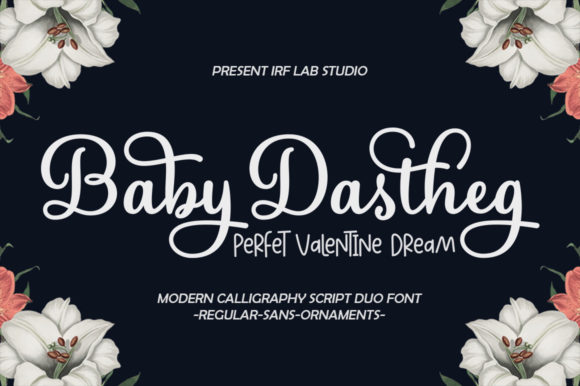
Baby Dastheg - это изысканный рукописный шрифт, мастерски разработанный, чтобы стать настоящим фаворитом.
Он сохраняет свое стильное каллиграфическое влияние, но при этом чувствует себя современным и свежим.
Влюбитесь в него и поднимите свои проекты на самый высокий уровень!